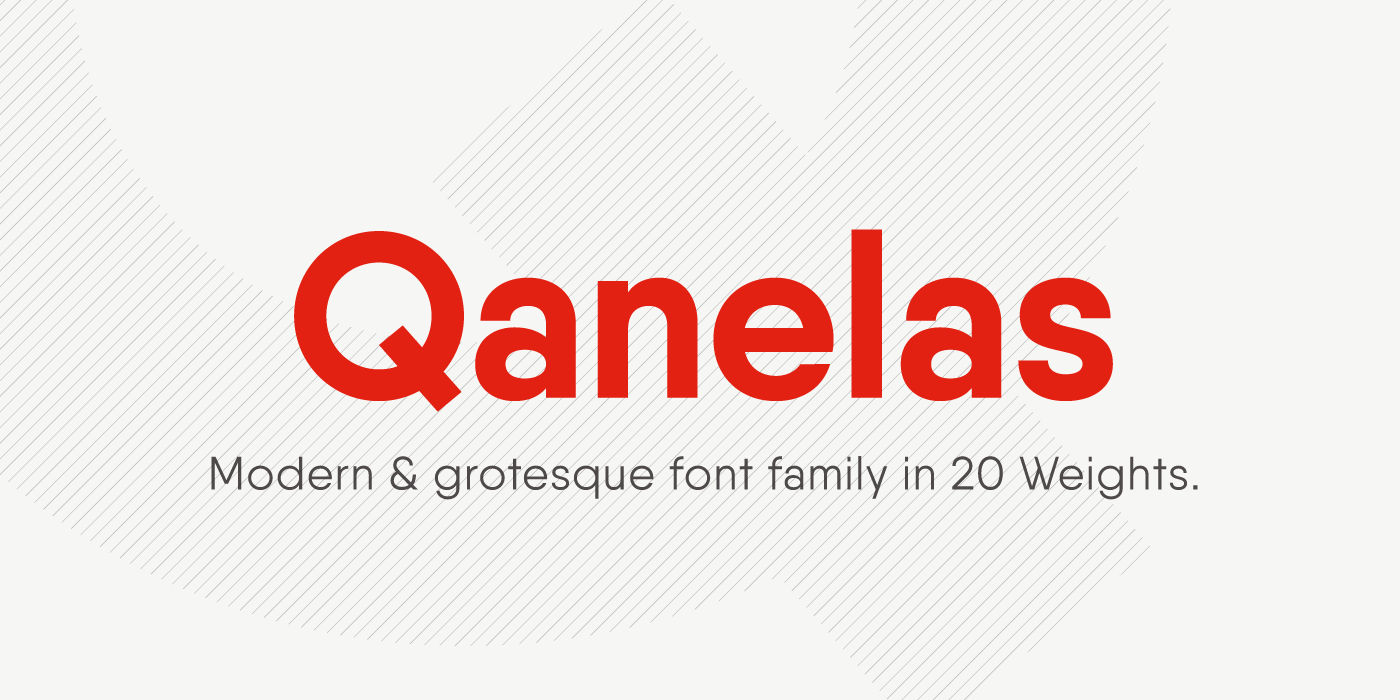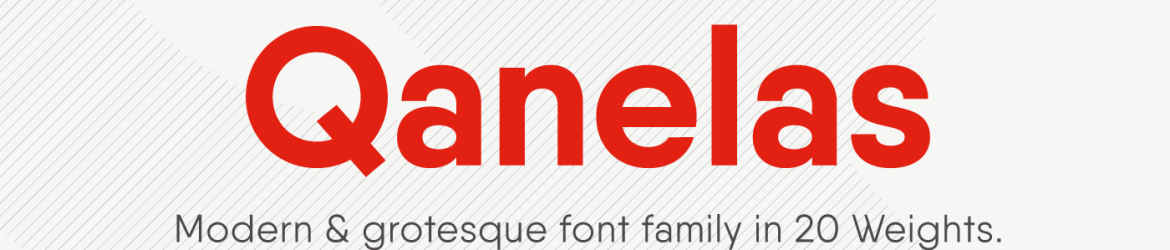
A Qanelas é uma fonte de tipo gótico moderna com toques geométricos que combina elegância pura com uma personalidade arredondada e alegre. Perfeita para um design que valoriza simplicidade e funcionalidade, esta fonte da família Qanelas é desenvolvida com uma paixão pela simplicidade do moderno, misturando um toque geométrico que adiciona uma dose de originalidade ao seu visual. Ela é uma fonte de tipo gótico que se destaca por sua versatilidade, oferecendo 20 pesos diferentes e 10 estilos uprights acompanhados de suas itálicas complementares. Seja você designer web ou gráfico, a Qanelas está aqui para dar um toque moderno e único à sua próxima criação.